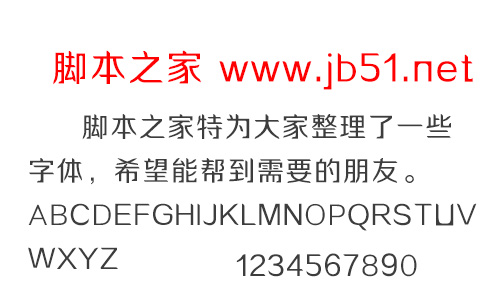
三極畫鉛簡(jiǎn)體是三極字庫(kù)推出的一款創(chuàng)意藝術(shù)字體,創(chuàng)意來(lái)自于鉛筆尖頭的外形,字形清新,結(jié)構(gòu)嚴(yán)謹(jǐn),起筆收筆都為斜角截?cái)啵卣髅黠@,整齊中賦予變化,易讀性強(qiáng)。適用于雜志、書刊、品牌廣告、文化用品包裝設(shè)計(jì),歡迎喜歡三極畫鉛簡(jiǎn)體字體的朋友前來(lái)下載使用。